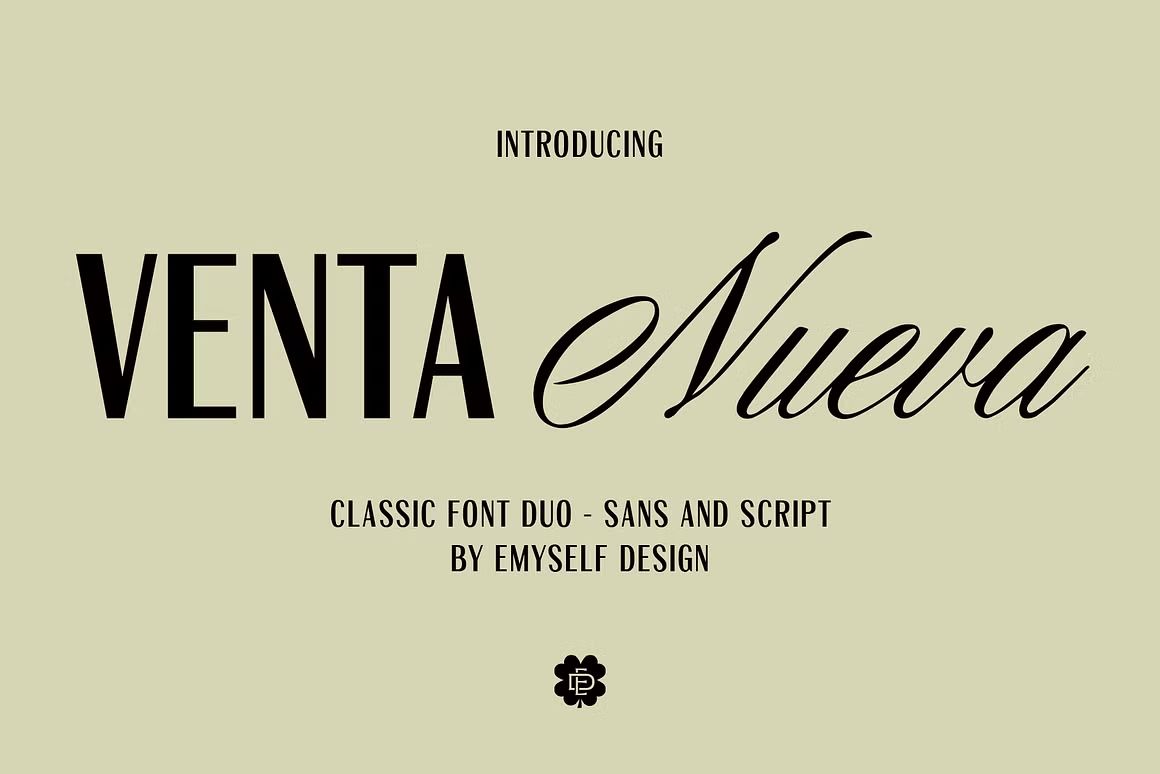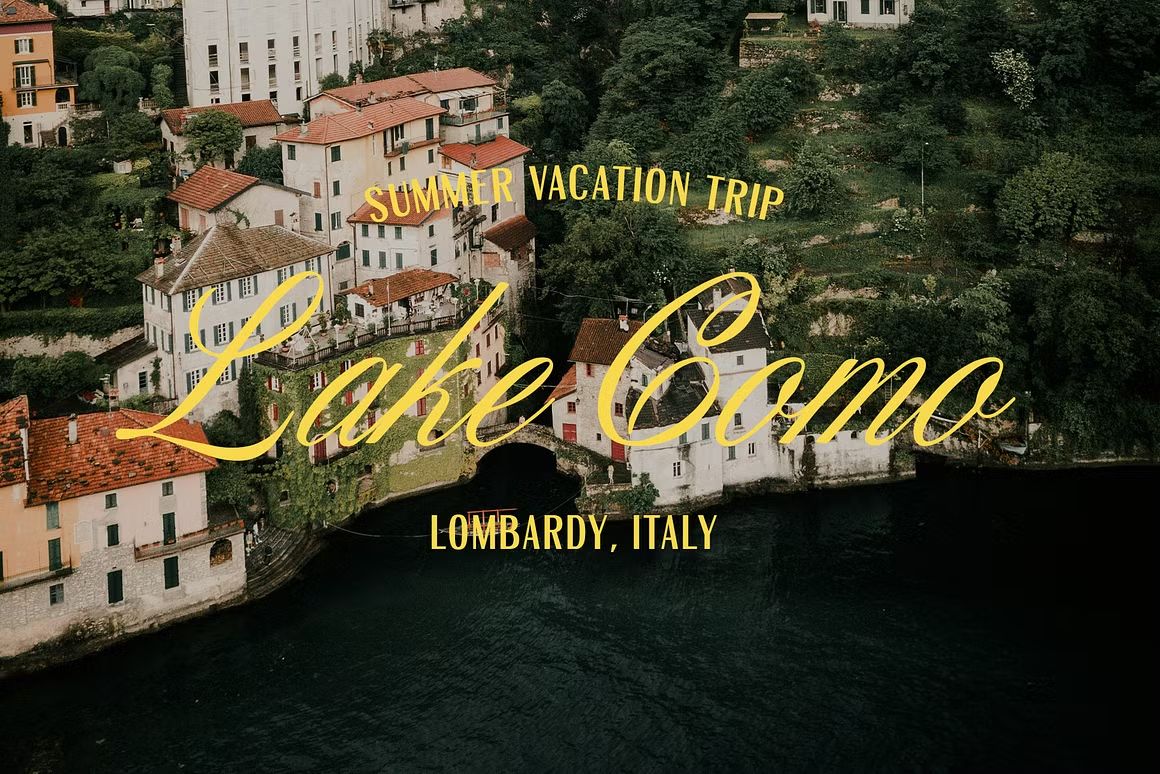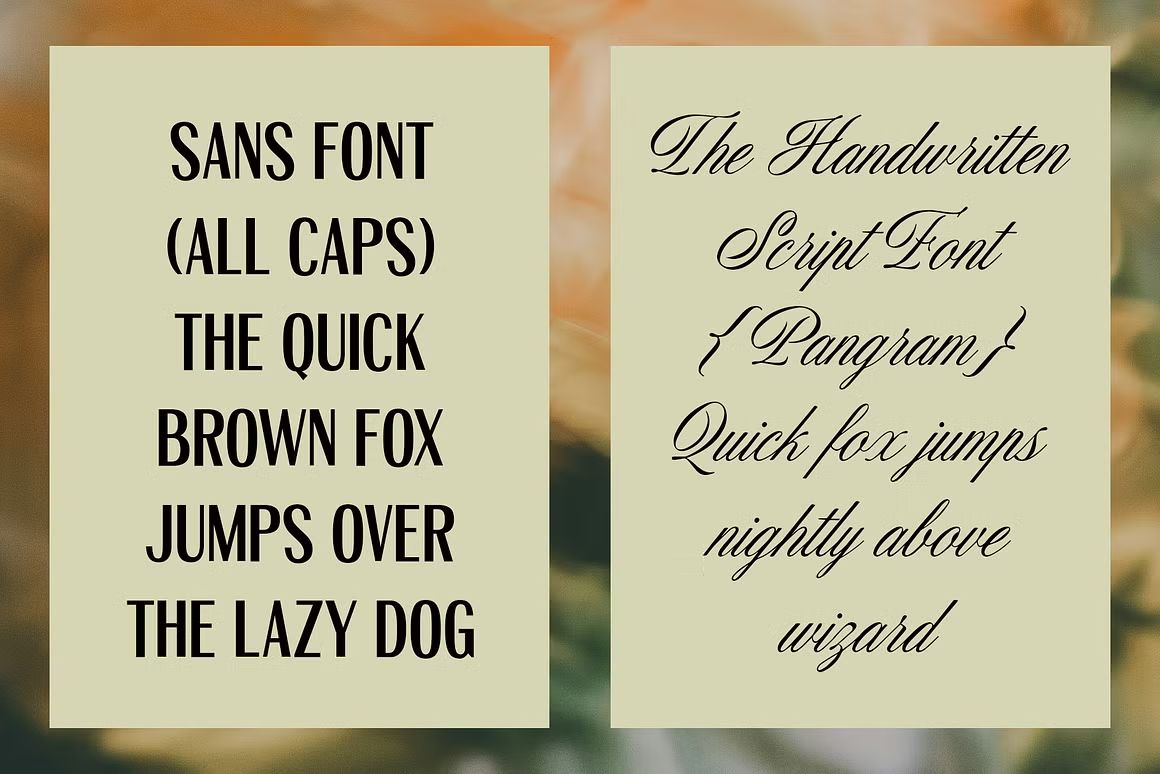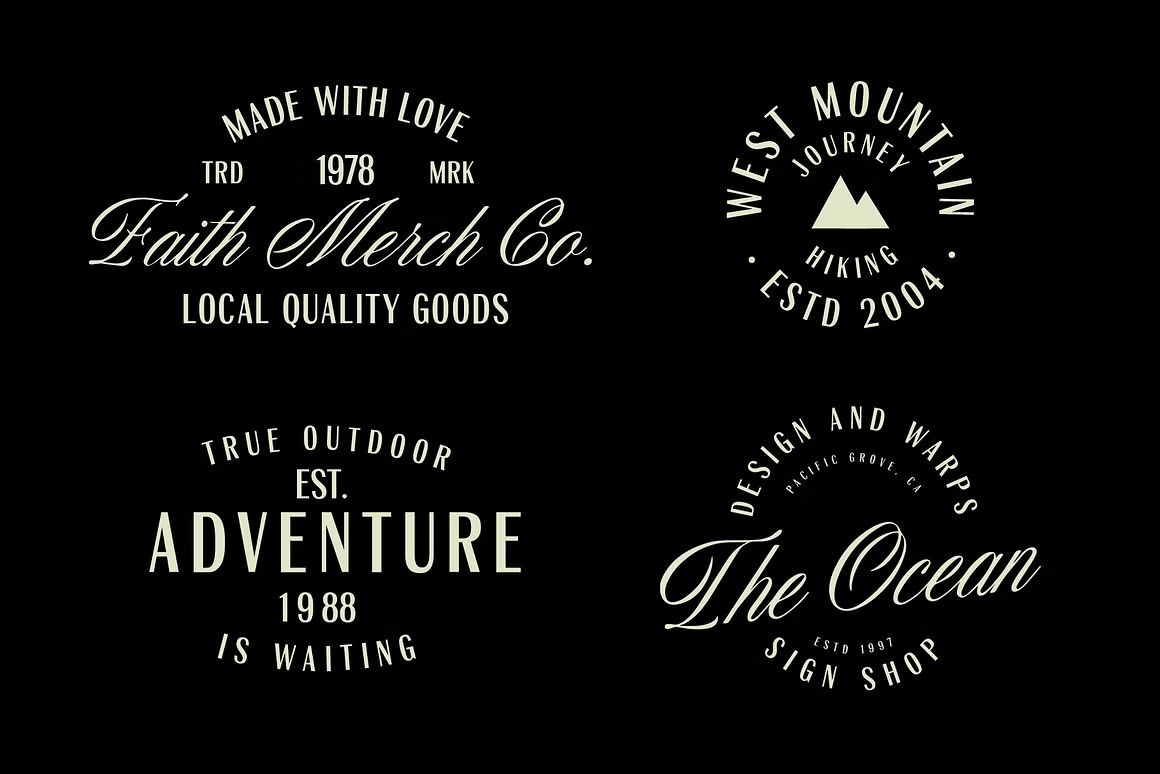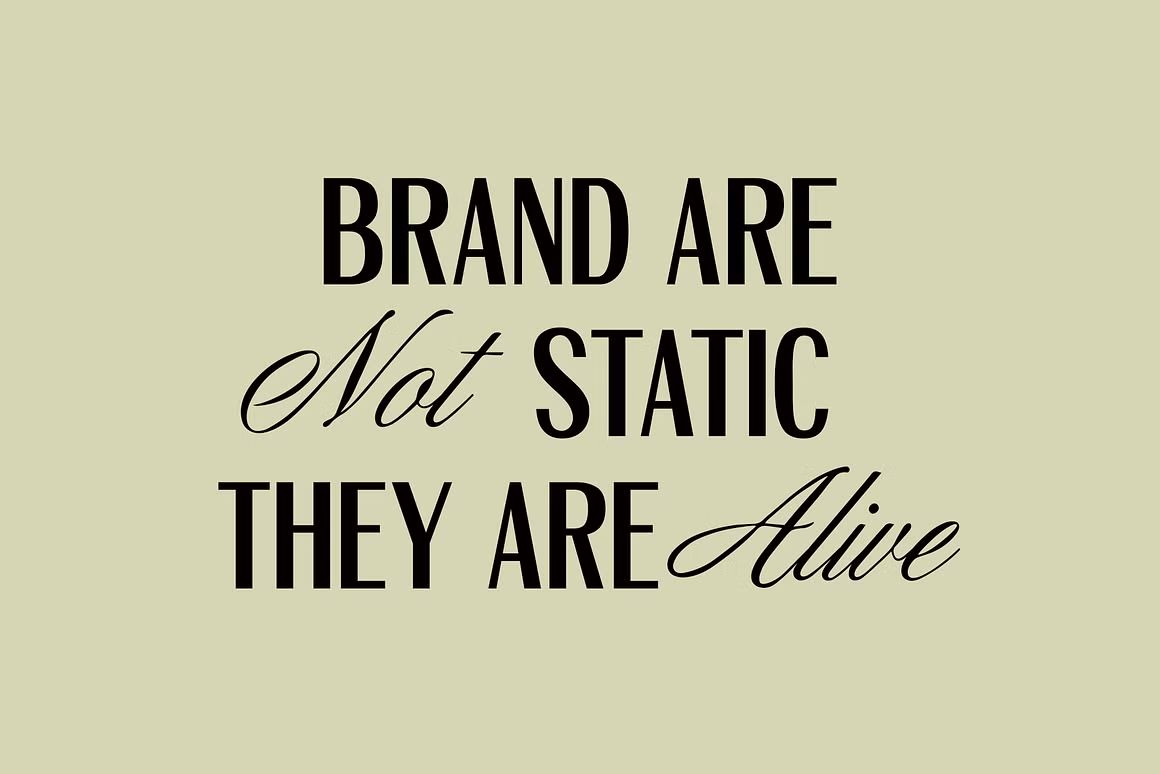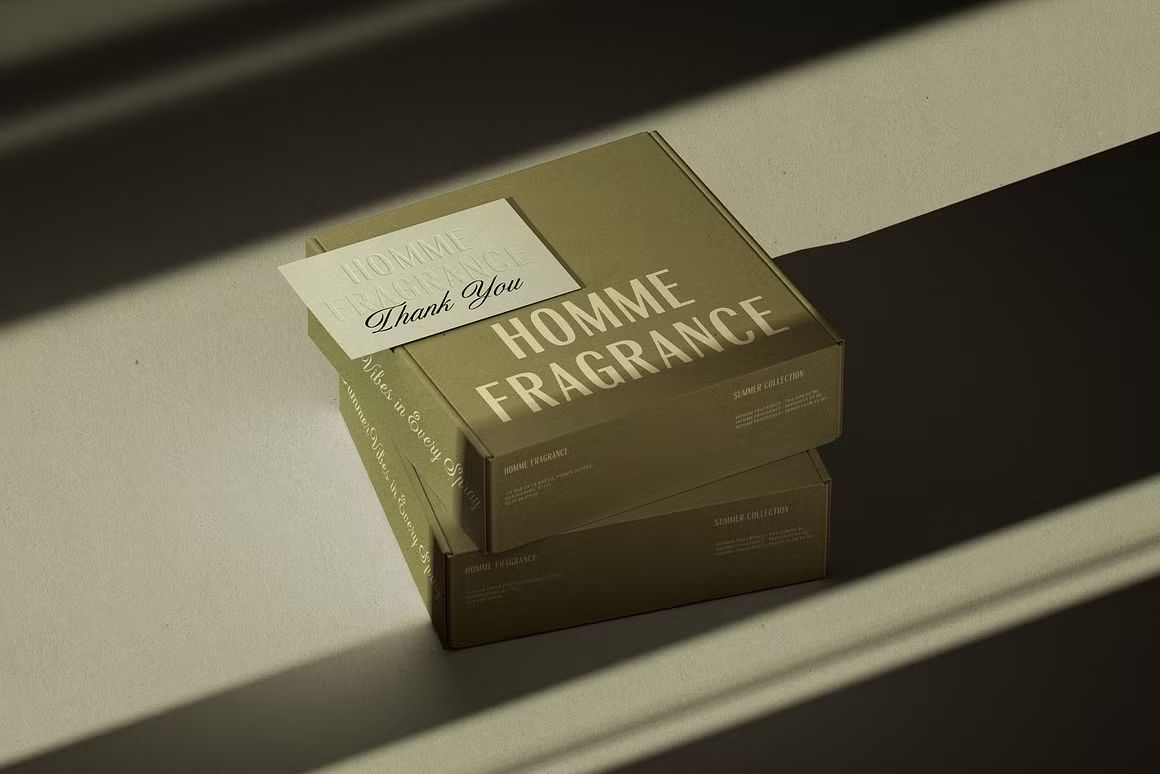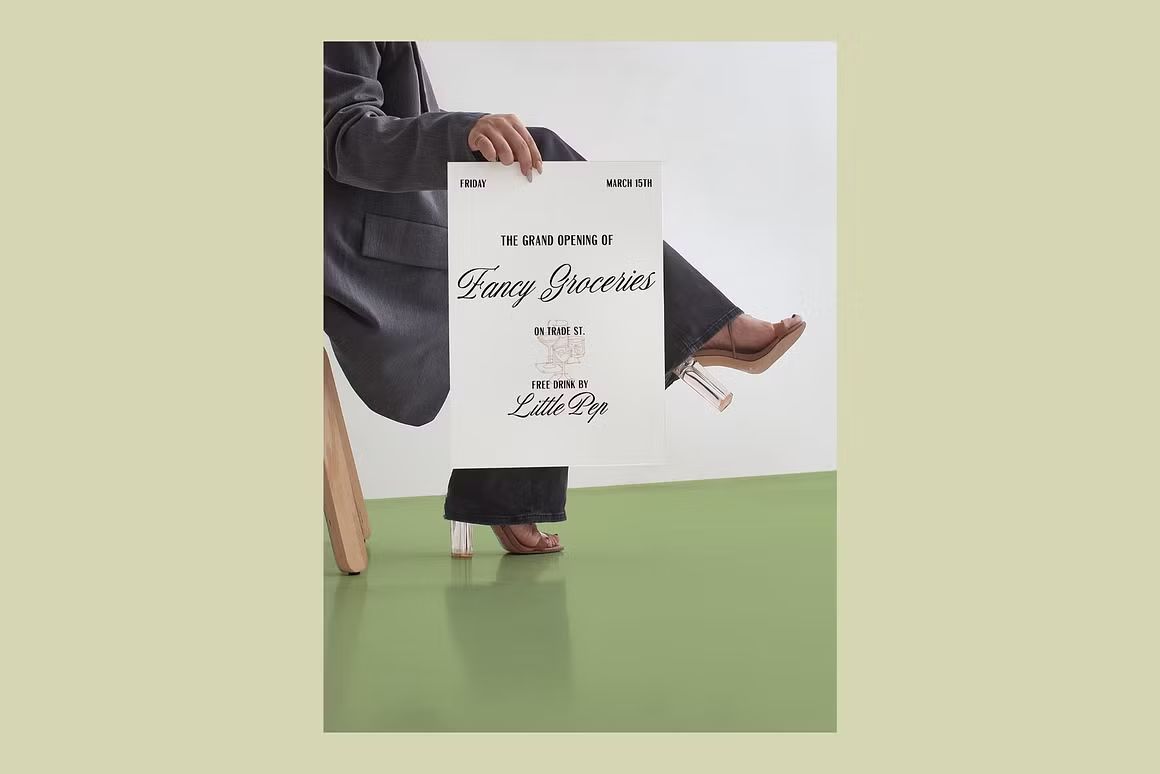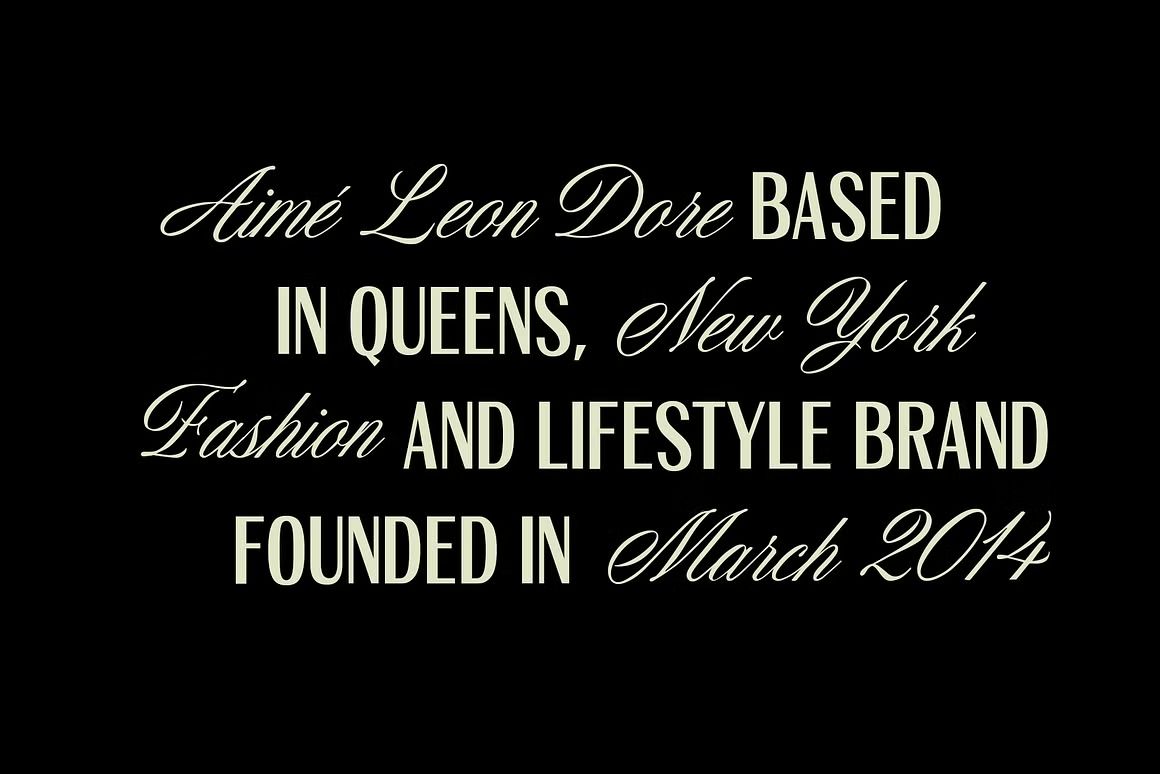
ED Venta Nueva – Script Font
ED Venta Nueva adalah font script vintage bergaya kuas tebal yang kuat dan berkarakter. Ideal untuk logo retro & desain klasik. Format OTF/TTF/WOFF, siap digunakan.
ED Venta Nueva adalah font script bergaya vintage dengan goresan tangan yang tebal, tegas, dan penuh karakter. Didesain untuk menonjolkan nuansa retro yang kuat, font ini sangat cocok untuk desain poster, label, logo klasik, apparel, dan signage bertema nostalgia. Garis-garis kuas yang dinamis dan detail kasar menambah kesan autentik dan berani, menjadikannya pilihan ideal untuk proyek desain yang ingin tampil standout.
• Script vintage dengan tekstur kuas tebal
• Cocok untuk logo retro, poster, dan desain berkarakter
• Lengkap dengan huruf besar, kecil, angka & simbol